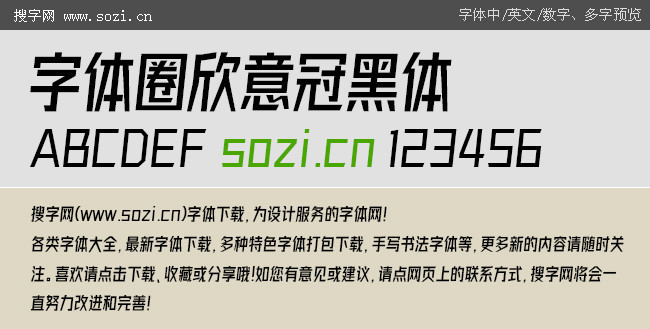
字體圈欣意冠黑體
搜字網(wǎng)給大家提供一款字體圈欣意冠黑體中文字體下載,這套字涵蓋國(guó)家GB2312標(biāo)準(zhǔn)的6763個(gè)中文字符,52個(gè)英文字符,10個(gè)阿拉伯?dāng)?shù)字,若干個(gè)中英文符號(hào),按需添加若干個(gè)生僻字,共7000余字符。因?yàn)樽中纹呤菪停瑴y(cè)試過(guò)這套字傾斜8°有點(diǎn)奇怪,最后選擇傾斜6°,視覺(jué)平衡多了。適合包裝設(shè)計(jì)、書(shū)裝設(shè)計(jì)、海報(bào)設(shè)計(jì)等應(yīng)用,此字體可免費(fèi)商用。